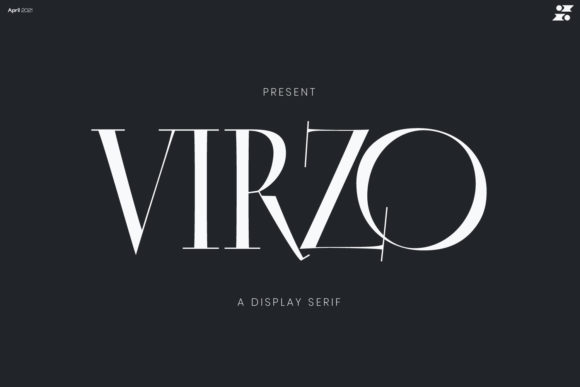
Creativefabrica Virzo Font
[Creativefabrica] Virzo Font
Virzo - элегантный, тонкий, высокий и модный шрифт serif.
Этот шрифт был специально разработан для тех, кому нужен красивый и освежающий вид их дизайна.